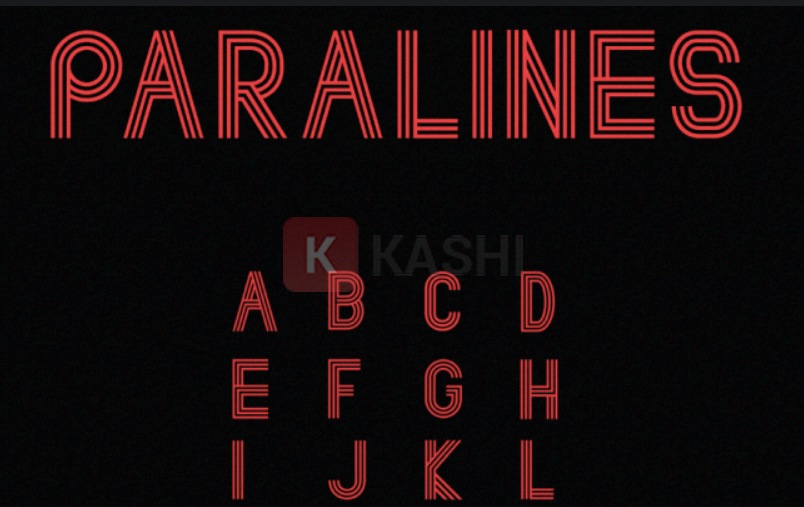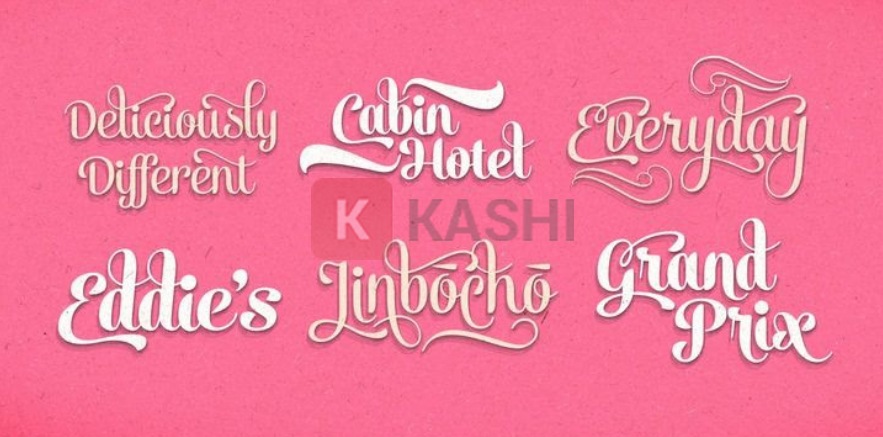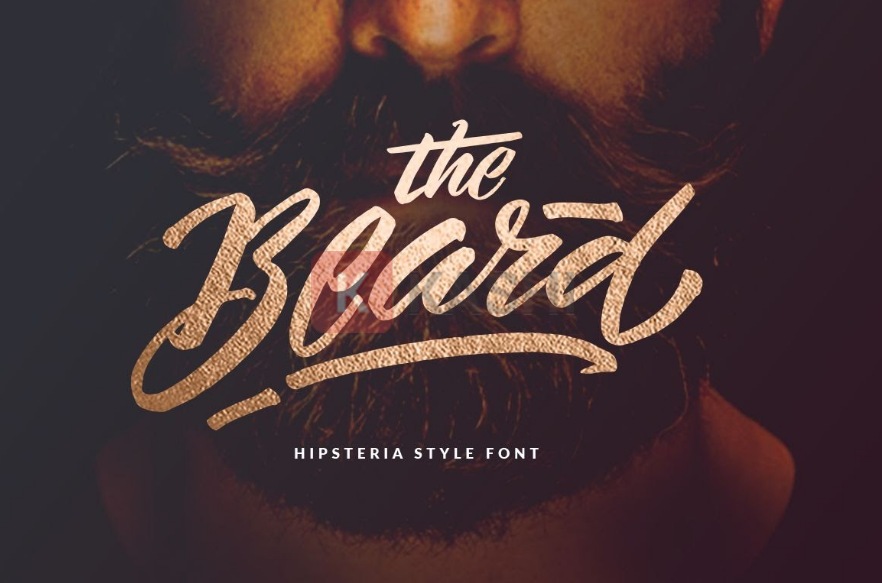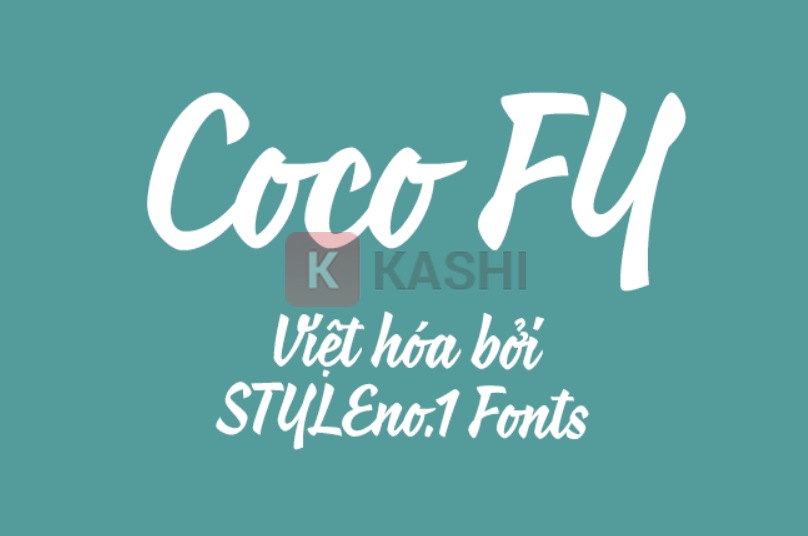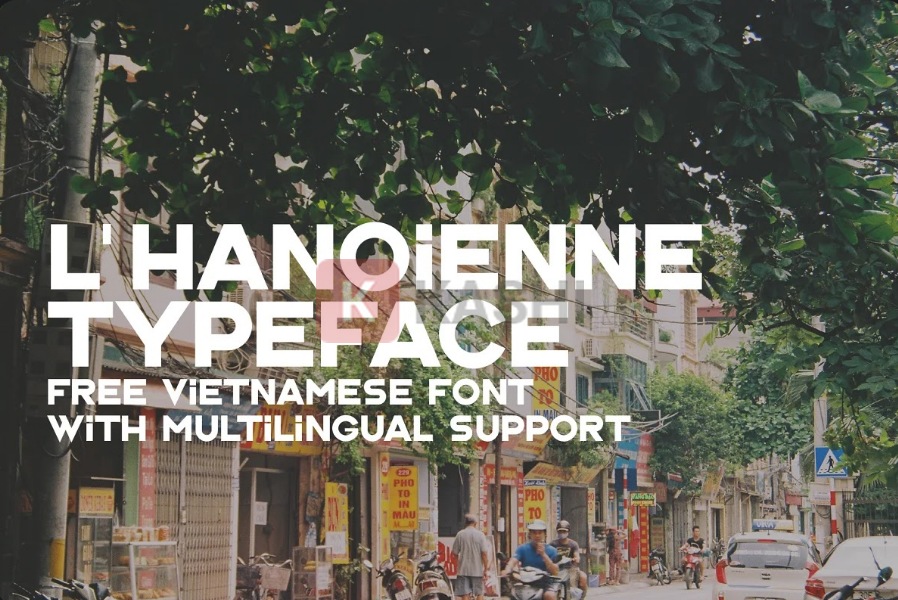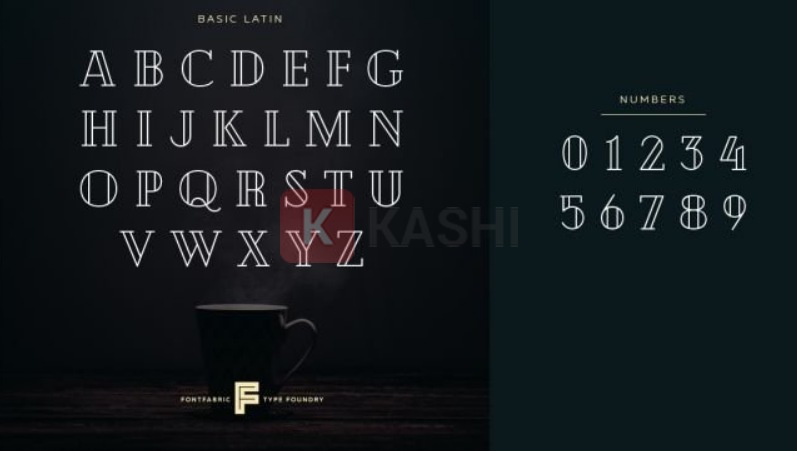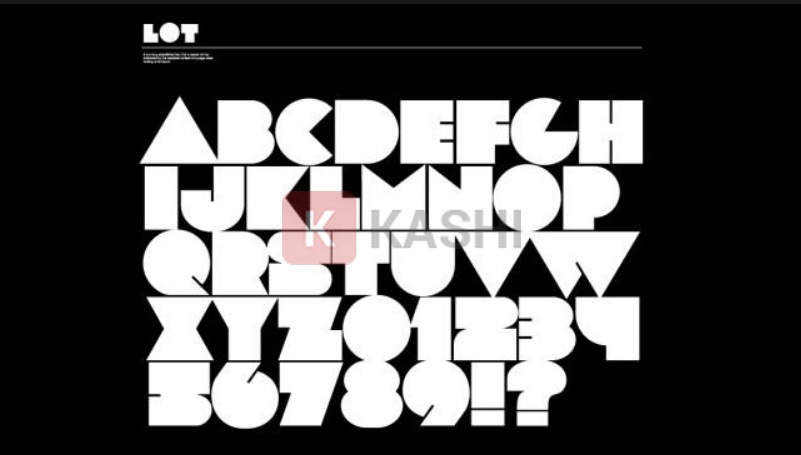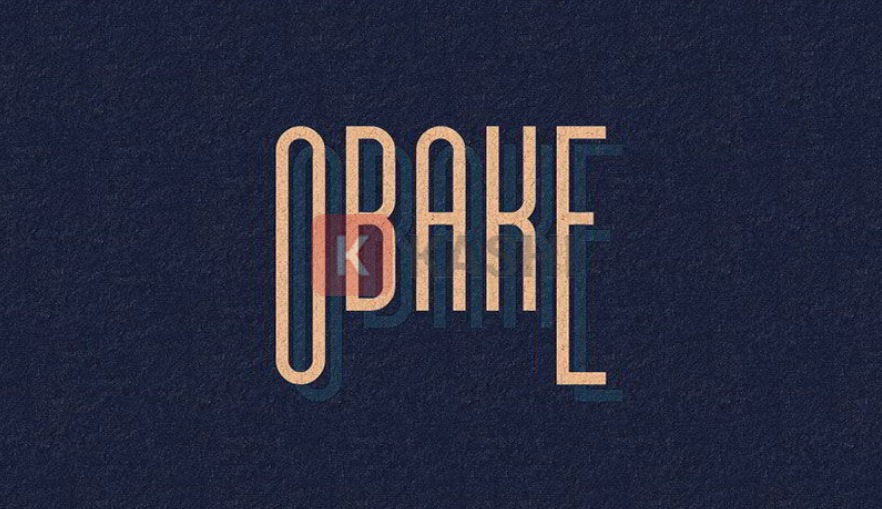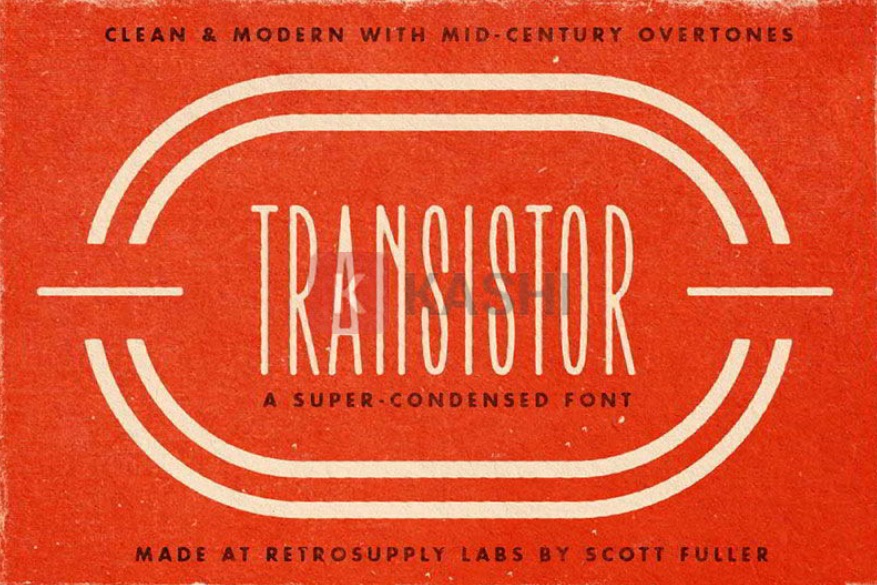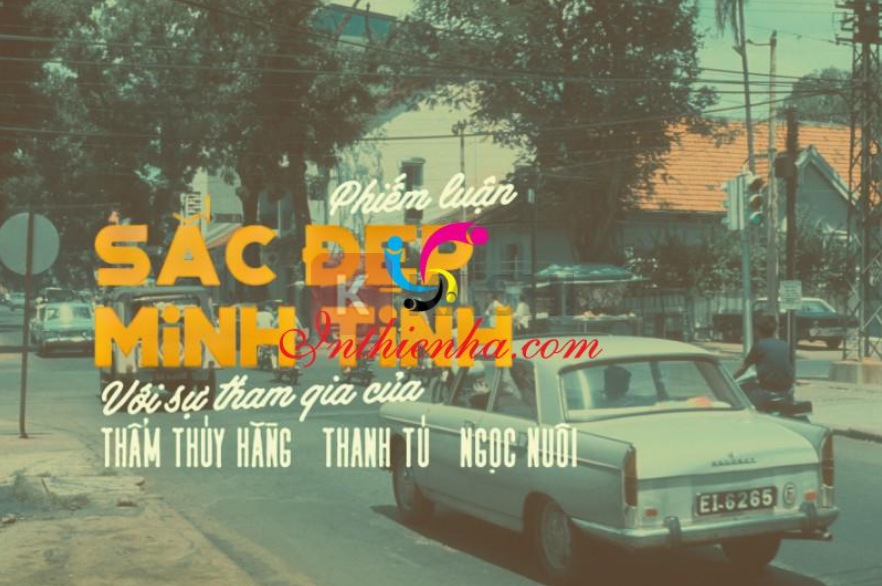
Top 15+ Font Chữ Vintage Việt Hóa Đẹp Nhất 2025
Phong cách thiết kế Vintage với nét đẹp hoài cổ đang rất được ưa chuộng. Đặc biệt, font chữ Vintage mang đến vẻ đẹp sang trọng, lãng mạn, đậm chất xưa cũ, được ứng dụng rộng rãi trong thiết kế. Bài viết này sẽ giới thiệu đến bạn đọc top 15+ font chữ viết tay Vintage việt hóa chất lượng, thịnh hành nhất năm 2025.
Font Chữ Viết Tay Vintage Là Gì?
Vintage là phong cách thiết kế được ưa chuộng trên toàn thế giới, thể hiện những đặc trưng cũ kỹ, cổ điển. Phong cách này thường được áp dụng trong thời trang, nhiếp ảnh, nội thất, thiết kế đồ họa,…
Font chữ viết tay (Handwriting Font) mang tính sinh động và cá nhân hóa cao. Các Designer thường sử dụng font chữ viết tay Việt hóa trong thiết kế đồ họa chuyên nghiệp, chỉnh sửa ảnh, thiết kế thiệp mời, banner,…
Ví dụ font chữ Vintage
Font chữ viết tay Vintage là hệ thống ký tự mang phong cách Vintage, với nét đặc trưng hoài cổ, xưa cũ. Trong xã hội hiện đại ngày nay, font chữ Vintage lại mang đến cảm giác gần gũi, thân thuộc cho người dùng.
Ứng dụng font chữ Vintage
15+ Font Chữ Viết Tay Vintage Việt Hóa Đẹp Nhất 2025
1. Font Chữ Cheque
Cheque là font chữ được Mirela Belova khởi xướng trên Fontfabric và sau đó được hoàn thiện. Font chữ này phù hợp cho phần tiêu đề (Headline) với hai phiên bản chữ thường và chữ in đậm.
Font chữ Cheque
2. Font Chữ Lot
Font chữ Lot có các nét chữ nằm trong khung hình học, tạo cảm giác mới mẻ cho phong cách Vintage. Với 78 ký tự, font chữ Lot phù hợp cho thiết kế Poster, logo và Headline. Đây là font chữ độc lập do FontFabric sáng tác.
Font chữ Lot
3. Font Chữ Obake
Obake là font chữ San Serif cô đọng với bóng cổ điển, rất đẹp mắt khi dùng làm tiêu đề. Font chữ này mang đến nét cổ điển của thế kỷ 17-18 cho các bản thiết kế.
Font chữ Obake
4. Font Chữ Nexa Rust
Nexa Rust là font chữ đầu tiên của dòng Nexa và Nexa Slab, bao gồm các kiểu sans, slab, script, handmade. Font chữ này là lựa chọn thích hợp để tạo nên các logo cổ điển.
Font chữ Nexa Rust
5. Font Chữ Transistor
Transistor mang phong cách retro Âu Mỹ những năm 70s, 80s. Nhà thiết kế đã tạo ra font chữ này từ những bao bì điện cũ được tìm thấy tại Los Altos, California.
Font chữ Transistor
6. Font Chữ Wallington
Wallington là font chữ serif cổ điển, thanh lịch, lấy cảm hứng từ văn hóa Anh giữa thế kỷ 12 và 19. Font chữ này tinh tế, tỉ mỉ và rất dễ đọc.
Font chữ Wallington
7. Font Chữ Coco FY
Coco FY được tạo bởi Bertrand Reguron & Gia Tran trên fontyou.com. Kiểu chữ này thường xuất hiện trên các bức tranh treo trong cửa hàng và bảng hiệu viết tay trên đường phố. Coco FY có độ tương phản cao và dạng font cô đọng, phù hợp làm Poster, bao bì, bảng biểu, logo.
Font chữ Coco FY
8. Classique Saigon Font
Classique Saigon mang đậm chất Sài Gòn xưa, được tạo bởi Mạnh Nguyễn. Font chữ này pha trộn giữa nét cổ điển và hiện đại, thường được sử dụng trong banner, backdrop, brochure, poster, video…